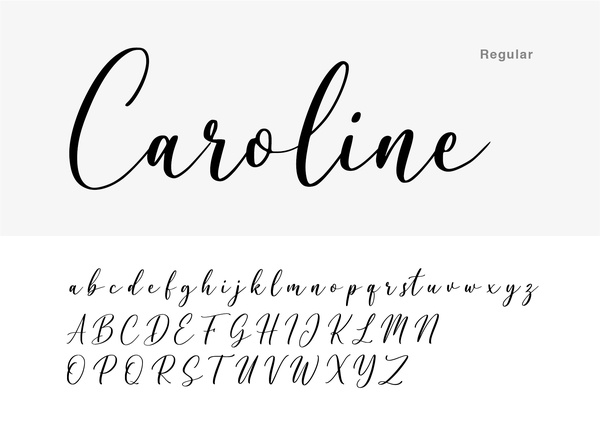
20 Font Calligrafici per dare carattere ai tuoi progetti
I font calligrafici da sempre ci riportano ad una scrittura senza tempo; le loro forme ed il loro stile particolare catturano immediatamente l’attenzione. Sinonimi di valore e prestigio possono aggiungere al tuo design un tocco di eleganza e fascino.
La calligrafia è una vera e propria forma d’arte che esiste da secoli, dalle sue radici nell’antica Cina fino ad oggi. Il termine “ calligrafia” è di origine greca e significa “ scrivere con bellezza”. Essa fornisce a ogni lettera carattere e personalità e per questo si rivela sempre molto espressiva. Non è sicuramente la forma di scrittura più leggibile e per ciò non adatta per l’utilizzo nel corpo del testo, ma se usata bene può creare grande impatto e dimostrarsi molto evocativa.
Oggi la calligrafia di un tempo viene ricreata con i cosiddetti font calligrafici o handwritten che imitano appunto la scrittura a mano. Essi possono essere utilizzati per i tuoi progetti grafici, specialmente se hai l’esigenza di una tipografia sofisticata o ricercata. Dunque, se sei un Graphic Designer che ha bisogno di ispirazione o se sei capitato qui per caso perchè in cerca di  font calligrafici che imitino la scrittura a mano, questo è l’ articolo che fa per te!
1. Aerotis – di Ef Studio
Aerotis è un font che cerca decisamente di farsi largo nella pagina, appuntito ma pur sempre aggraziato, difficile da leggere.
2. Amalfi Coast – di Typeline Studio
Amalfi Coast di Typeline Studio è un font davvero stupendo, aggrazziato, tondo e fine allo stesso tempo. Davvero ottimo per firme, difficle però da leggere.
3. Bailey – di NanaNissa
Bailey è un font corsivo di NanaNissa, molto aggraziato, abbastanza leggibile e perfetto per parole corte e memorabili, proprio per questo è ottimo per essere usato per nomi e brand.
4. Billion Dreams – di Mans Greback
Billion Dreams è un font davvero impattante, specialmente quando proposto in grassetto. Interessante per titoli, spettacolare sugli stampati come etichette e scatole, specialmente quando arricchito con una vernice serigrafica lucida spessorata.
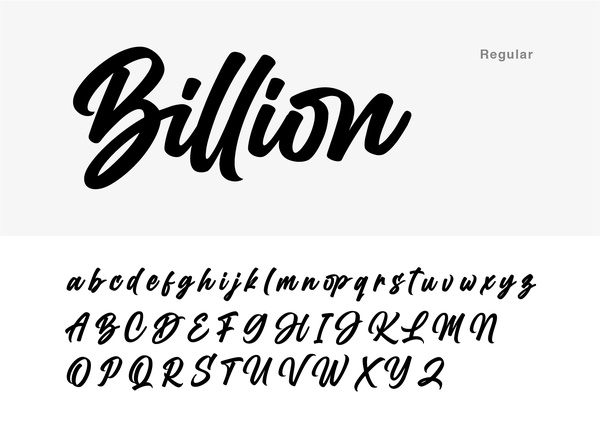
5. Brotherhood Script – di Youssef Habchi
Il Brotherhood Script è un font classico, personalmente molto da tatuaggi, anche se sfruttato nel modo giusto potrebbe risaltare su di una carta marcata naturale spessa, magari in debossing diretto sulla carta bianca!
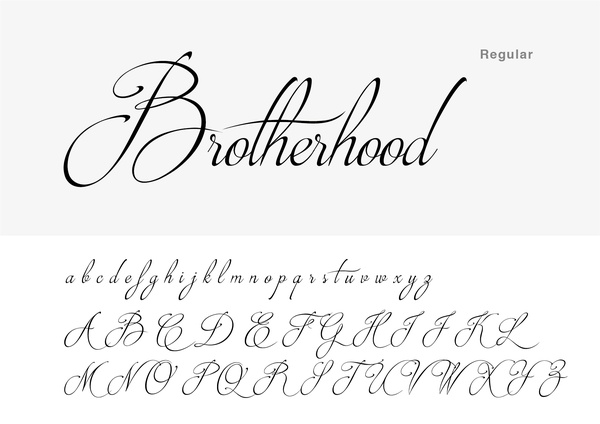
6. Caroline- di FatmaStudio
FatmaStudio ha creato Caroline, un font che ricorda molto un tratto a mano femminile e aggraziato.